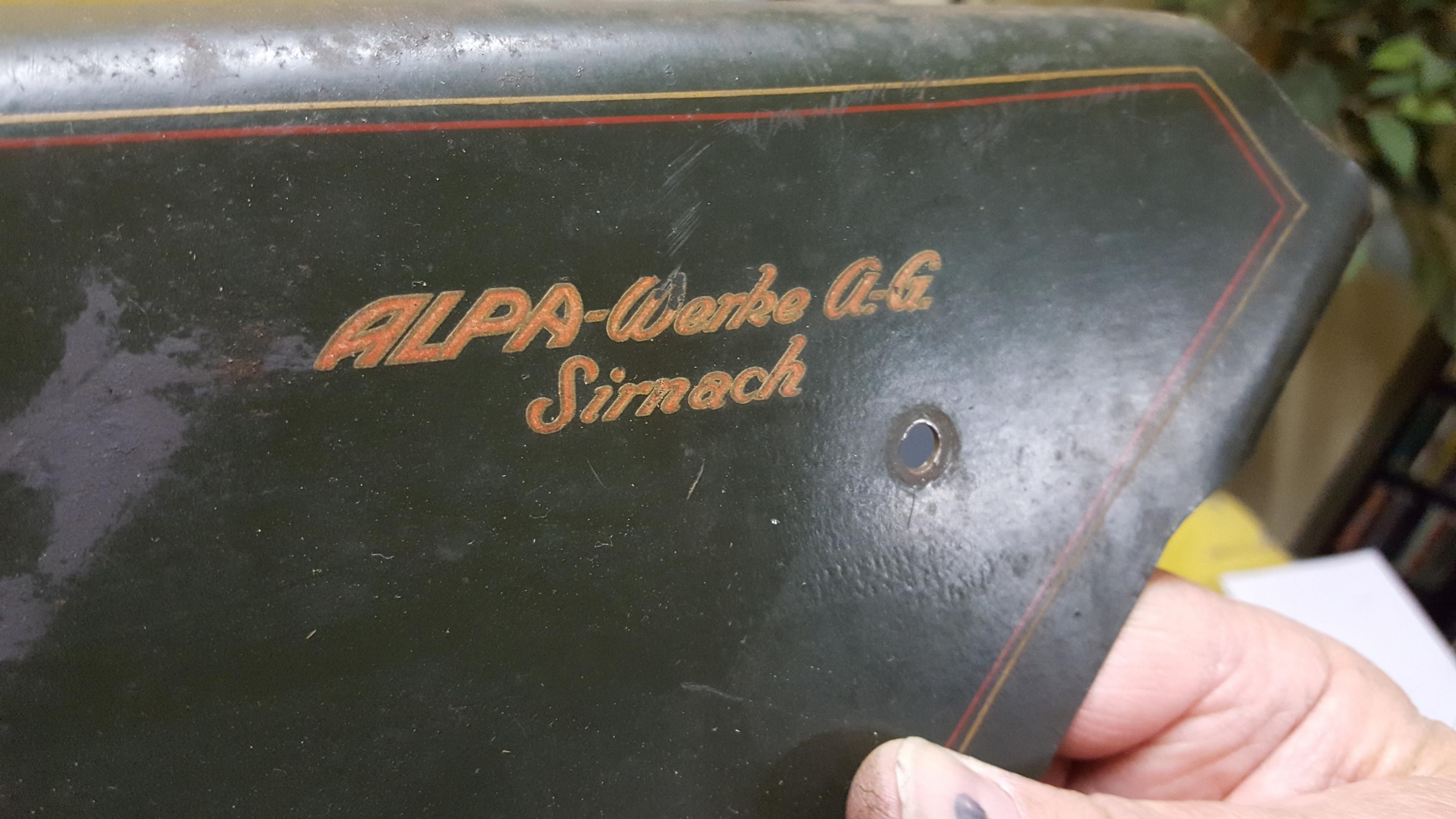
Schrift gesucht (50er Jahre)
Ich haben den "tollen" Auftrag angenommen, ein restauriertes Moped von 1954 neu zu beschriften.
Das Logo von dem Tank "ALPA" habe ich schon neu überzeichnet, aber auf den Schutzblechen seitlich ist diese Schrift drauf... und die möchte ich nicht unbedingt überzeichnen.
Kann mir jemand einen Tipp bezüglich der Schrift geben? Müsste eine Schreibschrift aus den 50er Jahren sein.
"Rechtman von David Rakowski" kommt dem noch am nähesten von denen, die ich gefunden habe. Aber vielleicht gibts ja noch was ähnlicheres.
Ich fürchte sehr, da wird es nichts geben.
Alles, was in dieser Zeit nicht auf Papier gedruckt wurde, wurde praktisch immer von Grafikern frei gezeichnet. Hier bleibt nur, das Blech auf den Scanner, und dann in Illustrator oder Corel oder Freehand oder Xara sauber nachzeichnen.